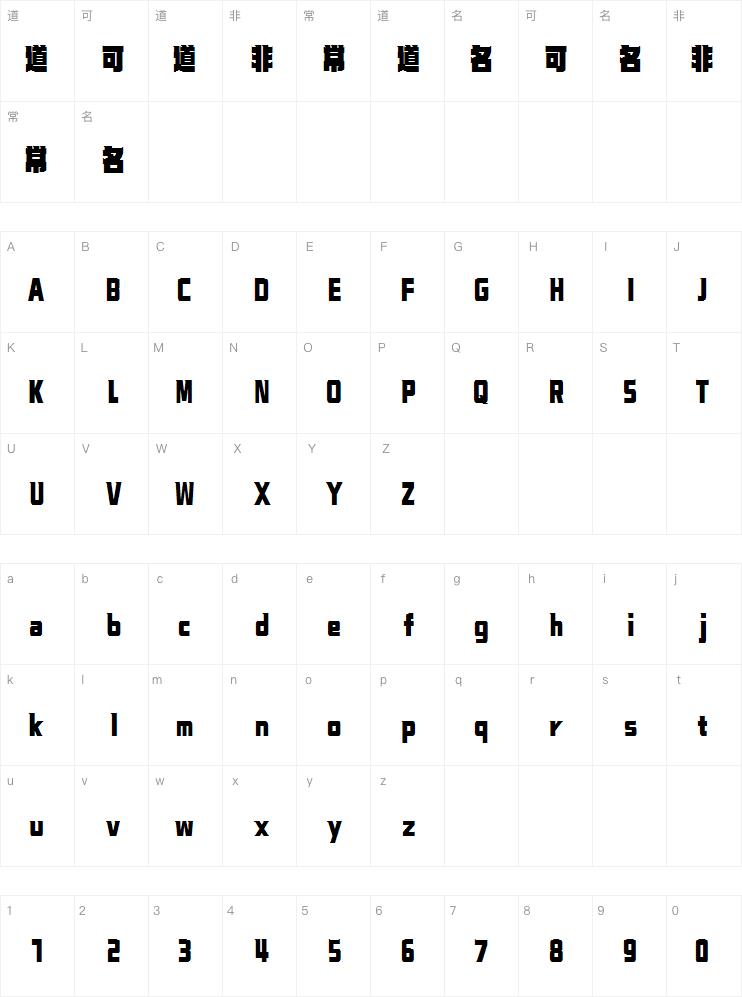
山海青锋正黑,是一款全新的字体,包含汉字9169个,符号200+个。该字体是一款综艺标题黑体字体,是一款具有强劲视觉冲击力的综艺风格标题字体。字形充实填满整个字框,造型硬朗,同时兼顾圆润性。直线与圆弧的笔画构成坚实有力,拥有宽大的中宫、粗厚且直线化的笔画设计、简洁明了的笔画尖角;字形比例按照宽高4:5的比例设计,使得字体显高;同时笔画带有尖角装饰,使得字形带有凌厉感,带来强有力的视觉冲击效果。该字体在综艺体的基础上做了诸多创新,使得该字体既有着流动的美感,又有着端肃的凝重,在正式用字场合落落大方,在日常使用环境中不失亲切友好,能够在保留综艺体基本特征的基础上更能适应当下时尚潮流的需要,助力各大新产品夺取标题主战场。